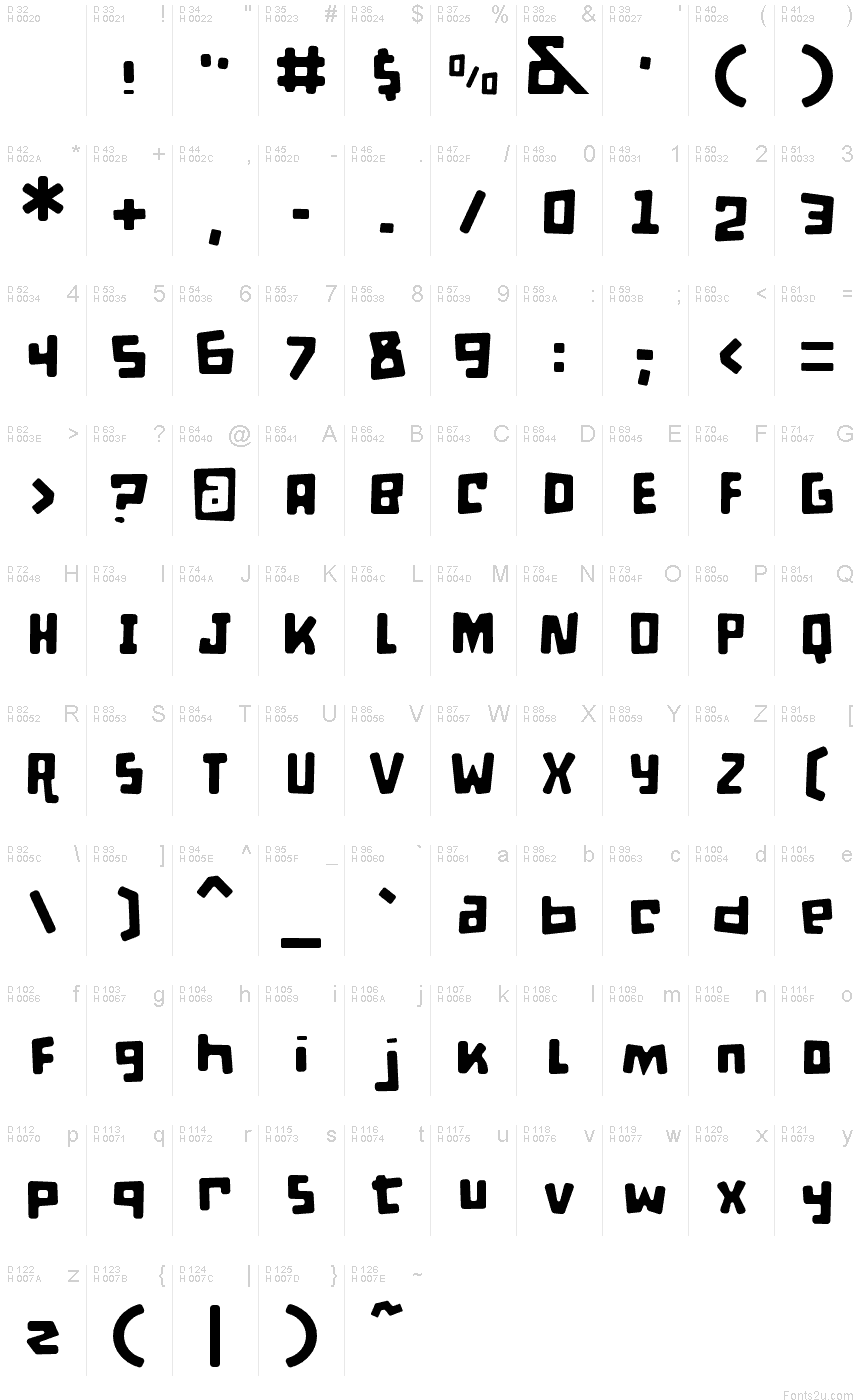
d puntillas [d] to tiptoe
d puntillas, a set of 6 combinable fonts, summer style and fun to design logos, typographical banners and posters or vector.
D PUNTILLAS [D] TO TIPTOE
La familia tipográfica "d puntillas" es un conjunto de 6 fuentes display combinables para la creación de títulos, púramente tipográficos, a dos o tres colores.
El desarrollo de esta tipografía surge de una propuesta, no aceptada, de un logotipo de 6 letras para un negocio llamado cactus. A partir del diseño original he creado el resto del alfabeto.
Y combinables también han sido los siguientes 3 conceptos por los cuales he nominado a este conjunto de fuentes:
Pasar d puntillas (to tiptoe): Tratar algo de pasada, sin profundizar ni insistir en ello.(DUE)... porque es un diseño tipográfico experimental.
Puntillas [a] (Lace): Encaje generalmente estrecho que forma ondas o picos en una de sus orillas y que se pone como adorno en el borde de pañuelos, toallas, vestidos, etc.(RAE)... por el aspecto de las letras con puntillas.
Puntillas de calamar (Tiptoes Squid): Caprichosos calamares de tamaño diminuto, lo ideal es tomarlos fritos con una cervecita, echando humo a la orilla del mar de un verano cualquiera y en honor a Joao Augusto, meu sobrinho brasileriro al que le gustan mucho las puntillas de calamar.